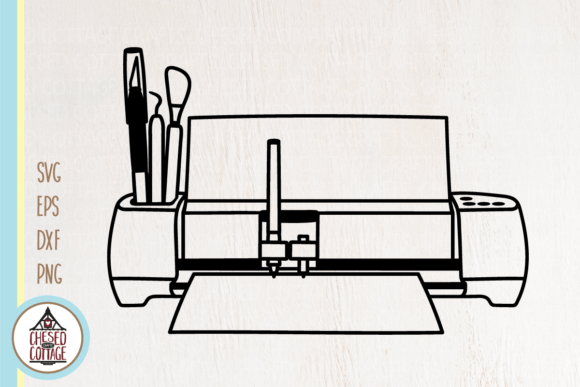
Crafting Machine
การค้นหาองค์ประกอบการออกแบบที่เหมาะสมอาจเป็นเรื่องท้าทาย แต่ Crafting Machine นำเสนอคอลเลกชันที่โดดเด่นซึ่งช่วยยกระดับงานของคุณได้ทันที
สร้างขึ้นอย่างแม่นยำ Crafting Machine ให้เวกเตอร์ที่สะอาด พิมพ์ตัวอักษรที่ราบรื่น และใบอนุญาตเชิงพาณิชย์เพื่อความสบายใจ
ไม่ว่าคุณจะสร้างผลิตภัณฑ์ POD (Print on Demand) คำเชิญงานแต่งงาน หรือกราฟิกโซเชียลมีเดีย Crafting Machine ก็เหมาะสมอย่างยิ่ง